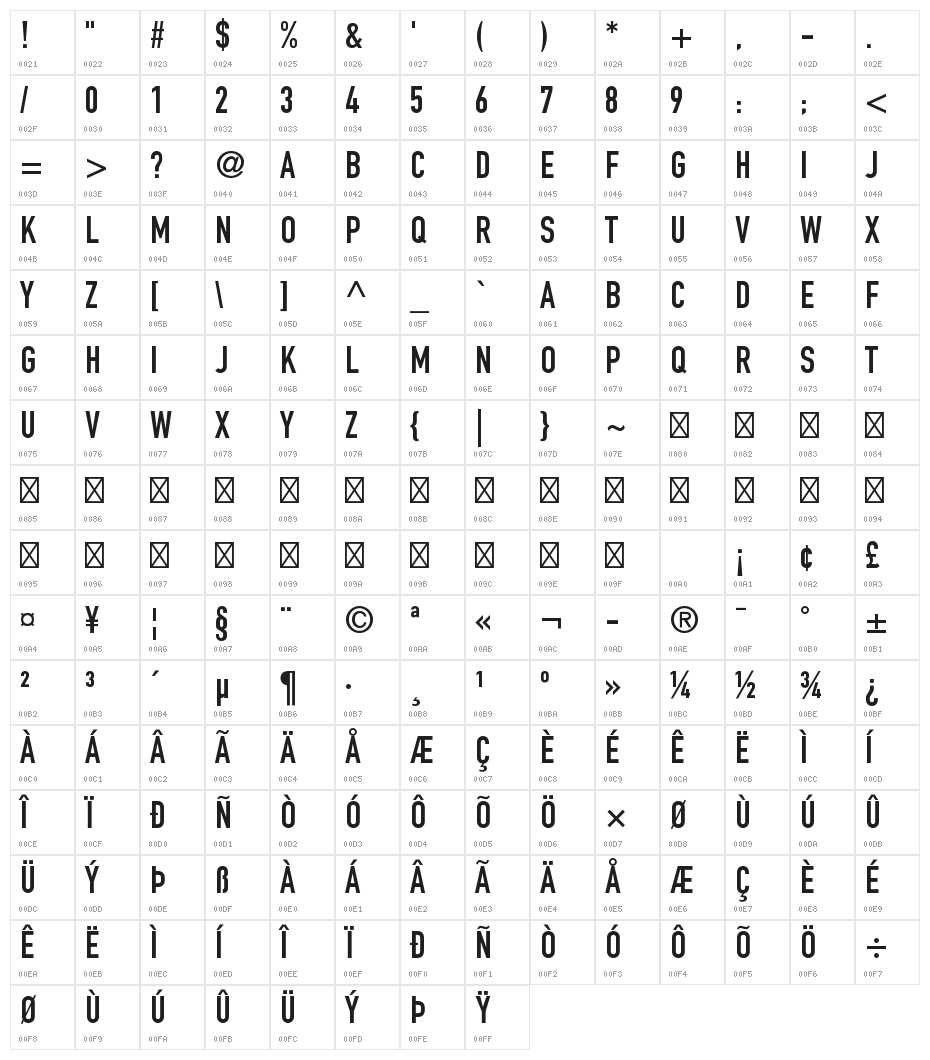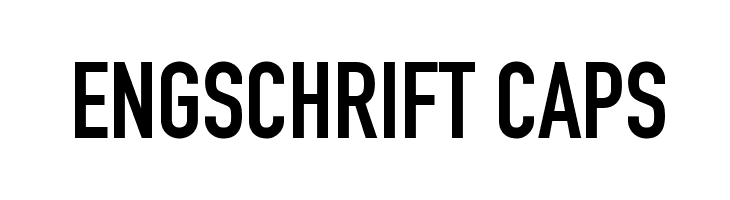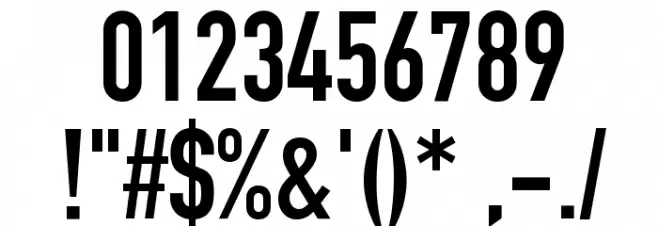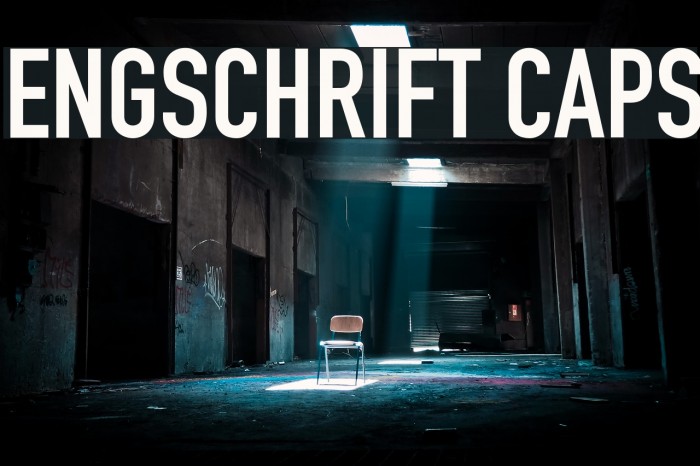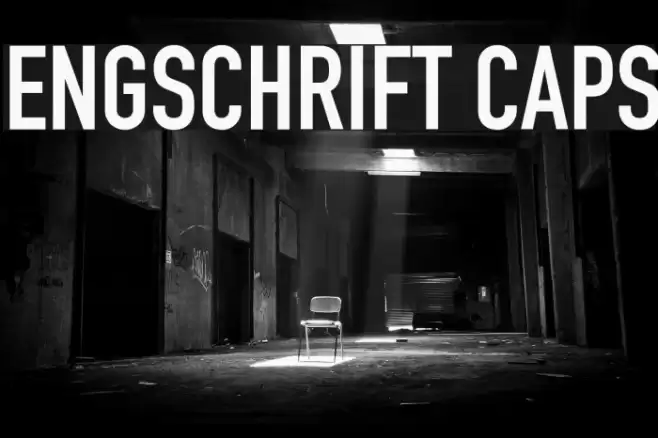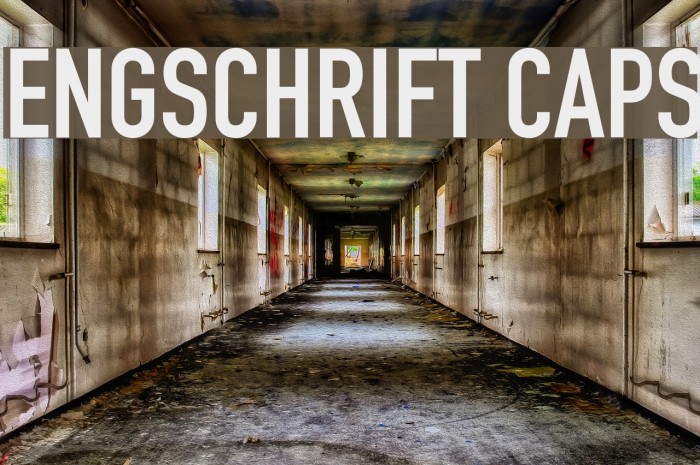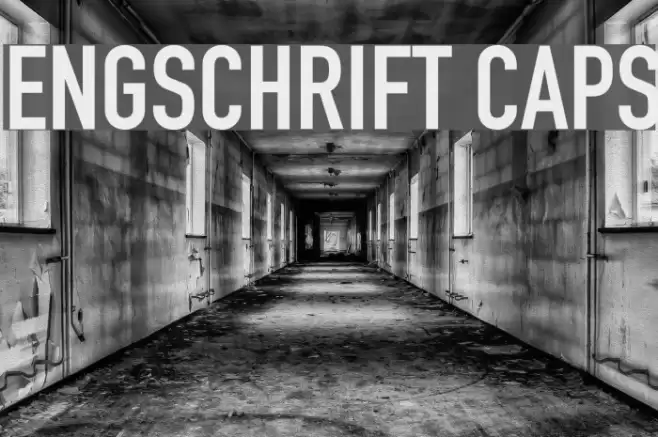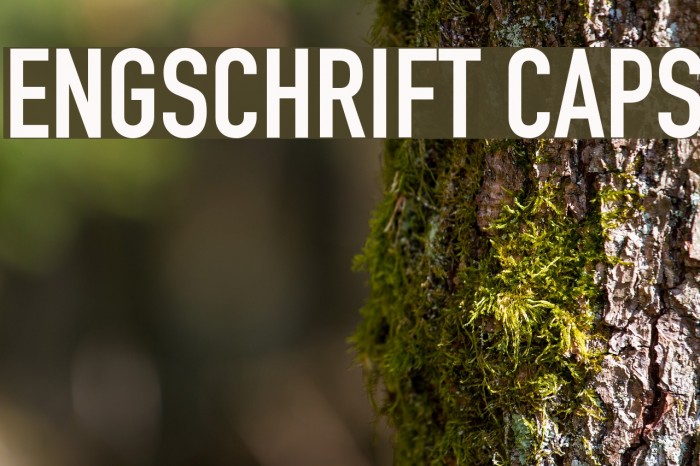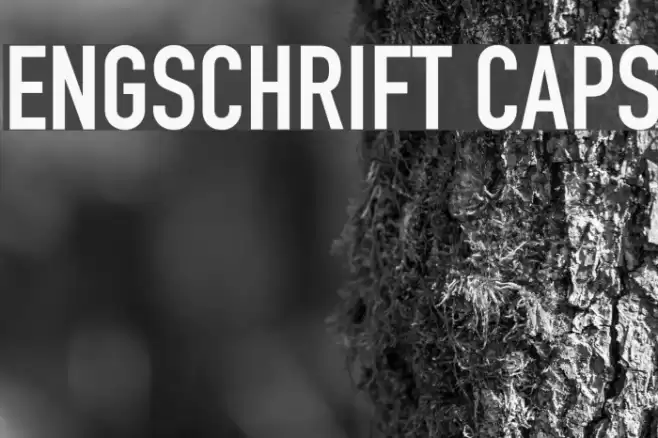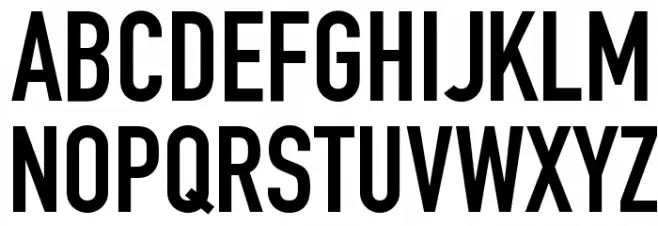
Engschrift Caps Font
| Caz de utilizare | Headlines, Logos, Signage |
| Proiecte propuse | Ideal for use in signage, posters, and branding where bold, clear messaging is essential. Suitable for transportation graphics, packaging, and editorial headlines. |